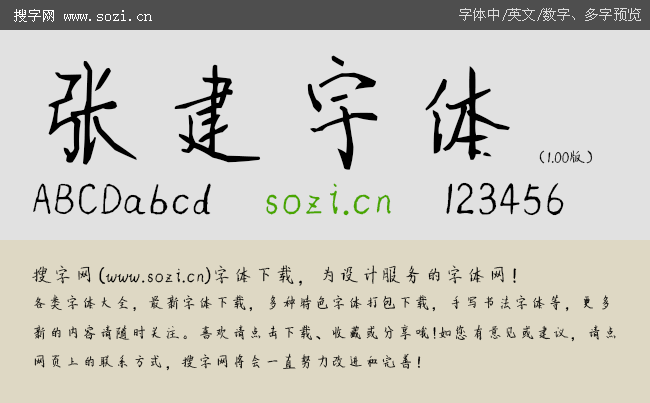
張建宇體
搜字網(wǎng)提供一款張建宇體中文書法字體下載,張建宇體是一款手寫風(fēng)格的鋼筆書法字體,字體書寫流暢,字形大方,整體效果十分出色,適合應(yīng)用于廣告設(shè)計(jì)、名片設(shè)計(jì)、包裝印刷、產(chǎn)品設(shè)計(jì)等應(yīng)用。